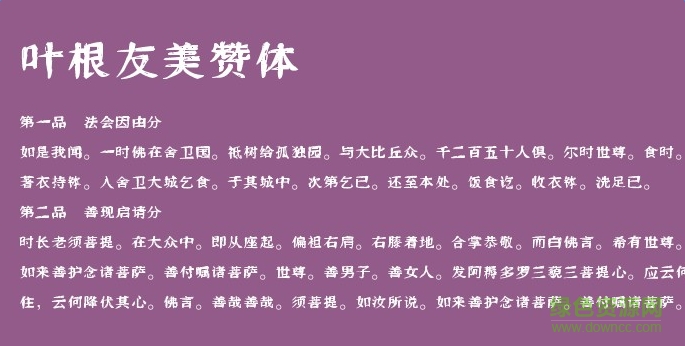
葉根友美贊體字體
葉根友美贊體是一款葉根友類簡(jiǎn)約清新風(fēng)格字體軟件,美贊體點(diǎn)與黑的巧妙搭配,令整個(gè)漢字靈活生動(dòng)起來,整體效果非??蓯?,還有更多好看字體歡迎來綠色資源網(wǎng)下載體驗(yàn)!
葉根友字體起始于2007年,定位手寫體,經(jīng)過7年的發(fā)展,已達(dá)30多套字體,目前已經(jīng)成為設(shè)計(jì)師必備字體,成為字體界繼方正、文鼎、漢儀后的一匹黑馬。 其中“葉根友美贊體”深受設(shè)計(jì)師喜愛。